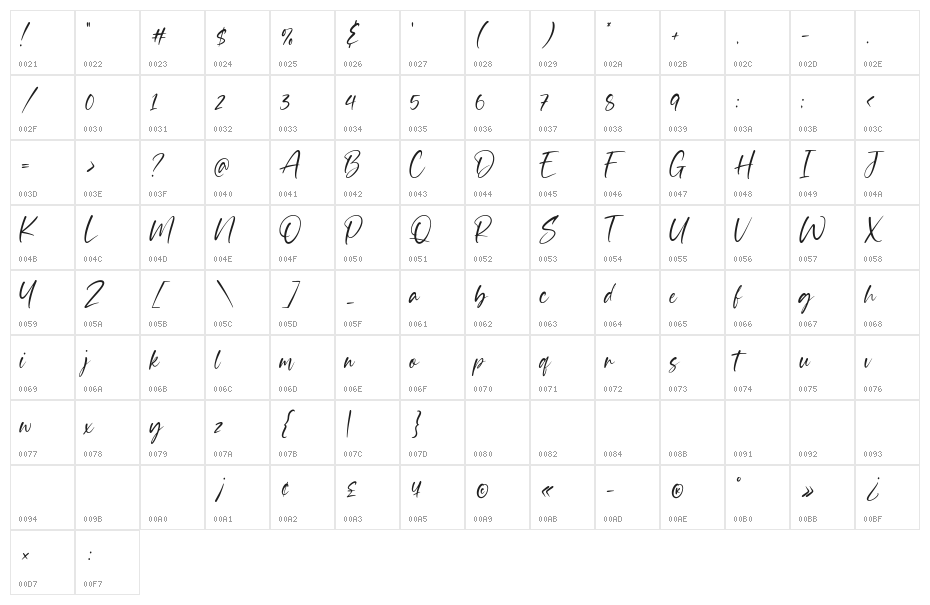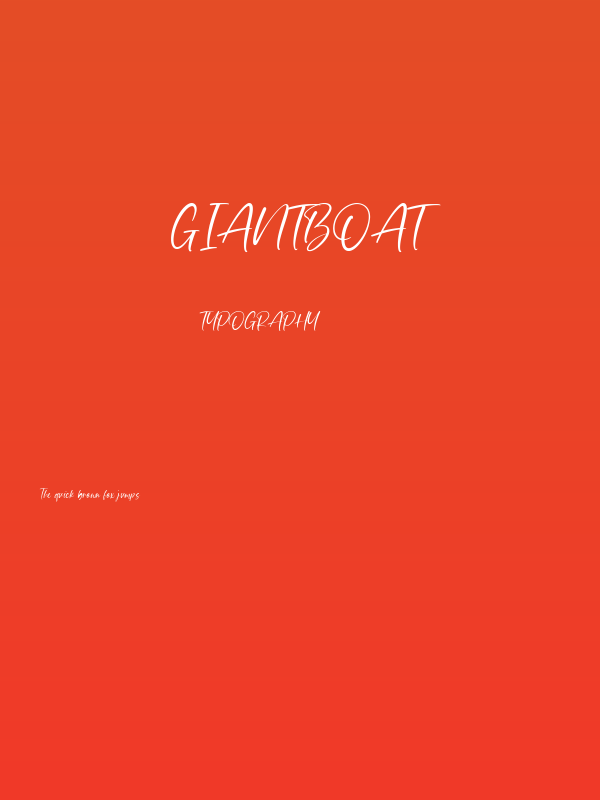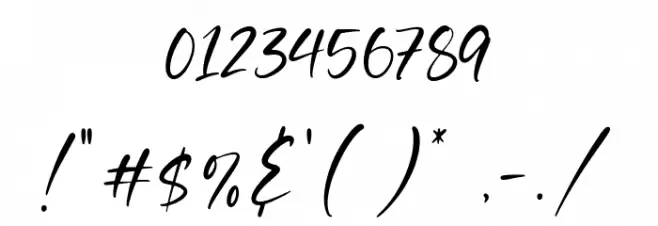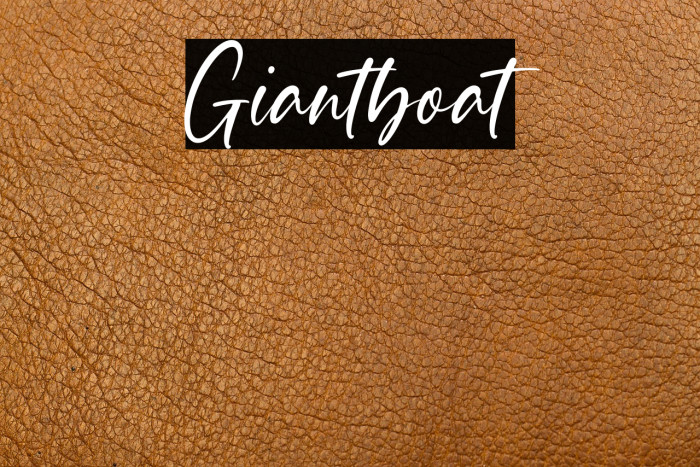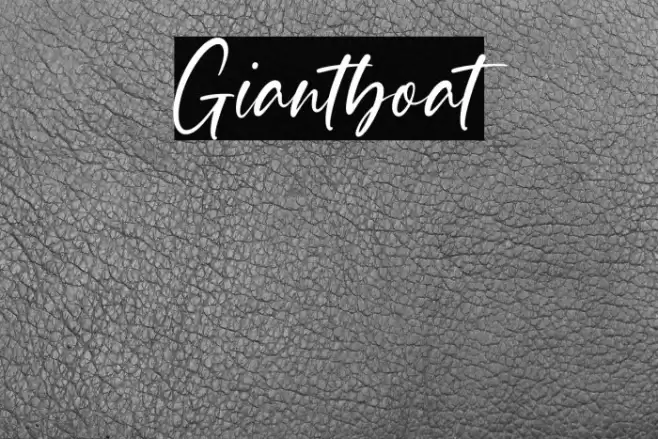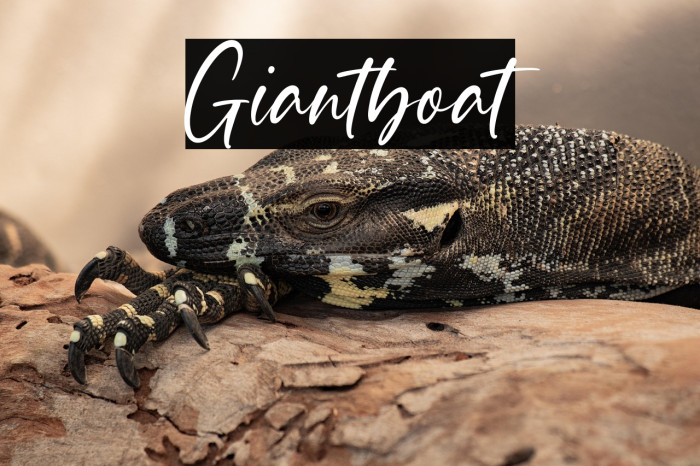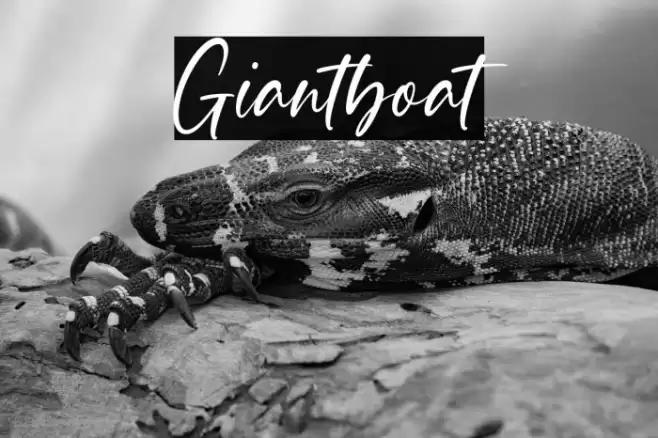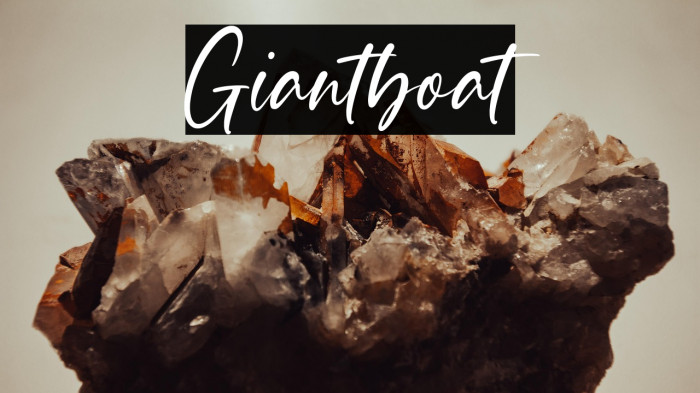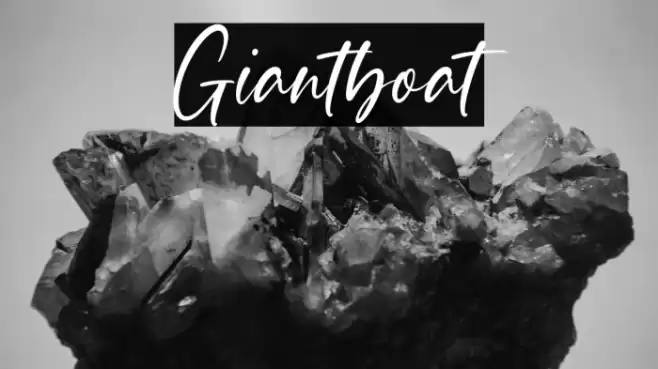
Giantboat Font
| Anwendungsfall | Logos, Headlines, Invitations |
| Vorgeschlagene Projekte | Ideal for wedding invitations, personal branding, greeting cards, and creative projects. |